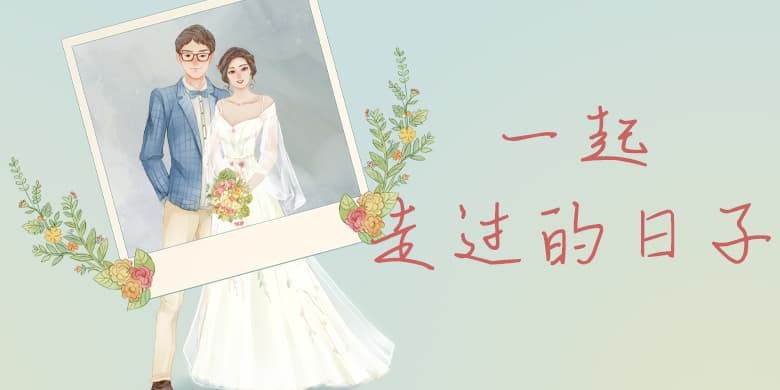
品牌:方正手迹设计师:王航发行时间:2020字库编码:大陆简体(GB2312-80)分类:常规书写·硬笔字体属性:精品字
一起走过的日子是一款文艺感十足的手写体。该字体笔画粗细统一,连笔流畅,松紧适中,笔画的舒展和连贯体现出字体的随性文艺。该字体适用于文艺类的书刊、品牌广告和产品包装设计,以及社交网络的个性化用字。